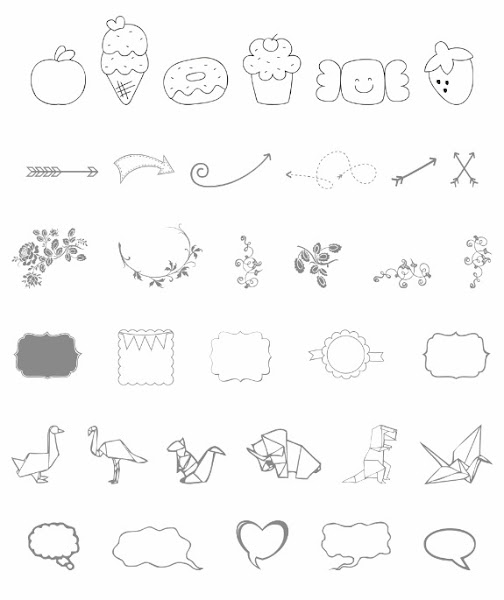
Tipografias molonas - Dingbats I
Ya estoy otra vez aquí para llenar tu ordenador de un monton de tipografías molonas y en esta ocasión un monton de dingbats que te van a servir para mogollón de cosas.
A mi los dingbats me vuelven loca, casi mas que las tipografías que ya es decir... jejejejeje
No las uso tanto para diseños, laminas o cositas de ese estilo, que también ojo!, pero me centro en ellas para carvar sellos, o hacer plantillas para decoraciones. Es un poco mas complicado pero si tienes algo de maña te salen piezas super chulas y así no tienes que tener millones de troqueladoras por ejemplo.
En cuanto a los diseños y laminas de lo que mas tiro son de marcos, coronas de flores, flechas... que vienen muy bien si no tienes mucha mano para diseñar y ademas oye! que te ahorra un monton de tiempo que ya estén hechas.
Vamos con ellas!
Ainsss que bonitas son todas verdad? ^^
Yo de la de dibujos kawaii y de los animales de origami ya los tengo hechos casi todos en sellos jejejeje de hecho puedes verlo en mi instagram, aquí el helado y aquí el proyecto del donuts.
Pero todas son perfectas para carvar. También la de las flores son ideales para hacer unas laminas bonitas para el salón, las flechas para hacer identificadores de sitios en una boda por ejemplo. Vamos! que las posibilidades son infinitas, yo las uso para muchas cosas.